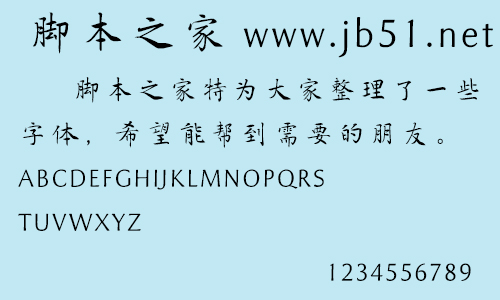
方正管峻楷書簡(jiǎn)是一款書法家管峻先生創(chuàng)作的字體,這款字體輕巧自然,結(jié)體以褚遂良書法為本,參以己意自成一家,工穩(wěn)清麗,其風(fēng)格秀美空靈,適合應(yīng)用于藝術(shù)設(shè)計(jì)、平面宣傳設(shè)計(jì)、網(wǎng)頁(yè)設(shè)計(jì)等領(lǐng)域,需要的朋友可以前來(lái)本站下載。